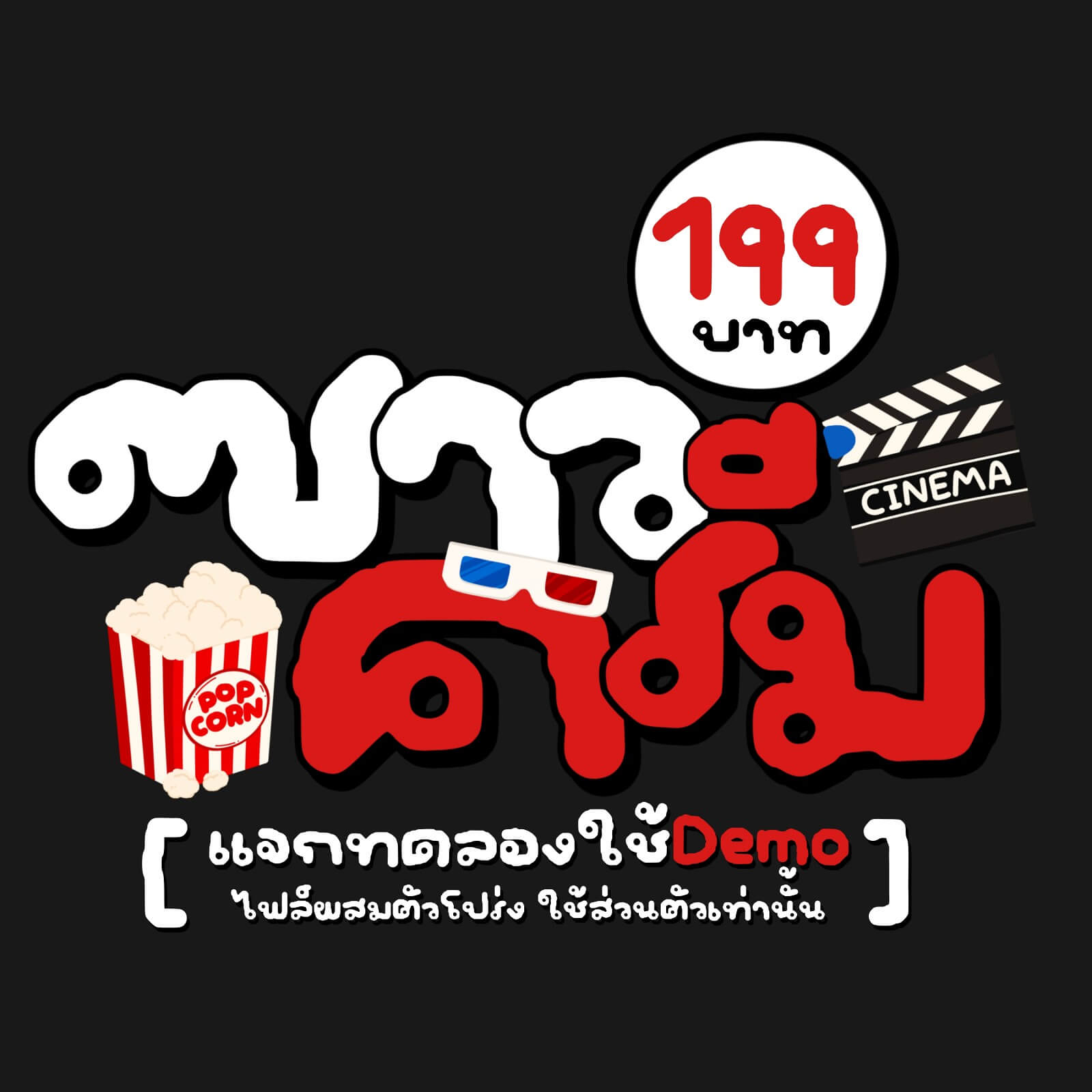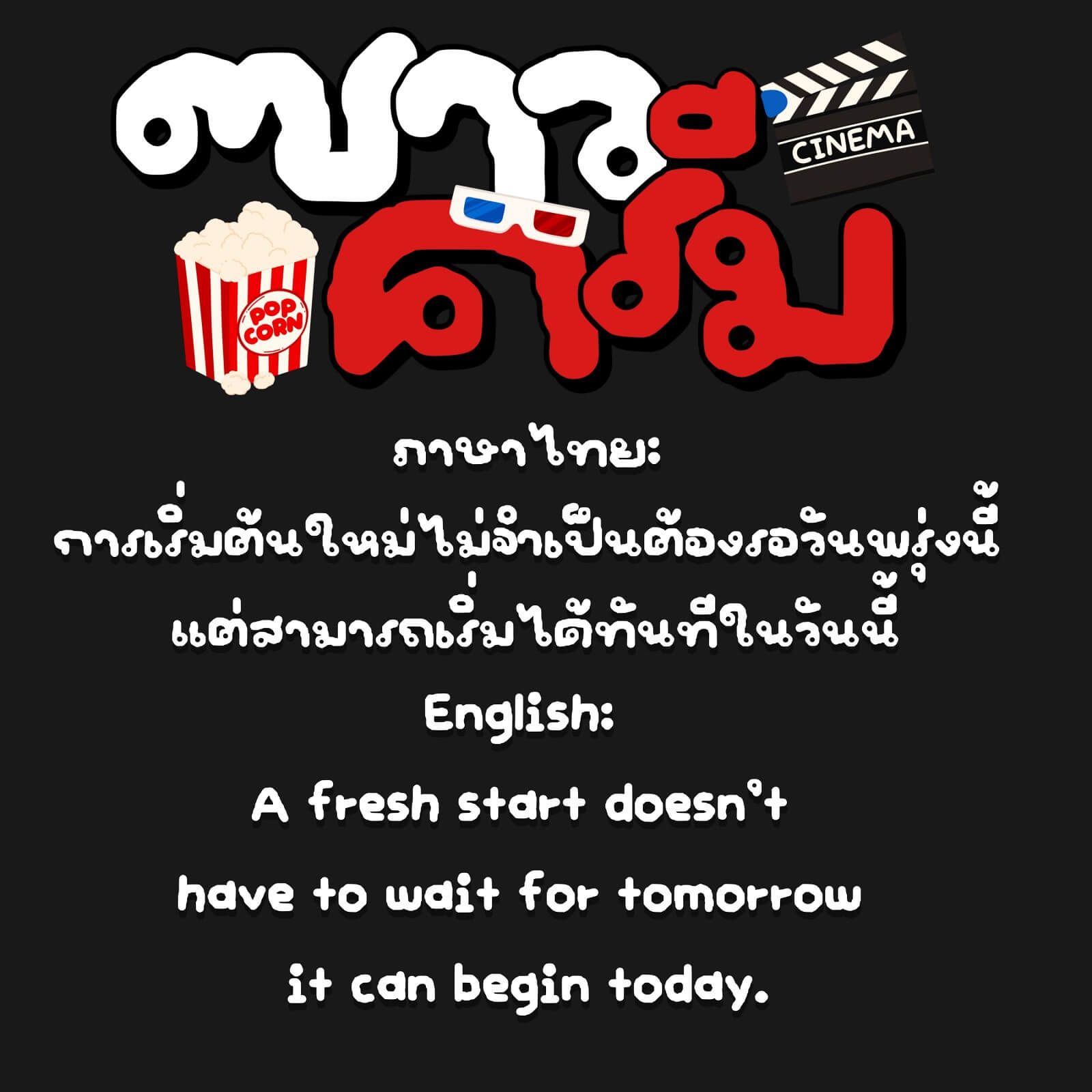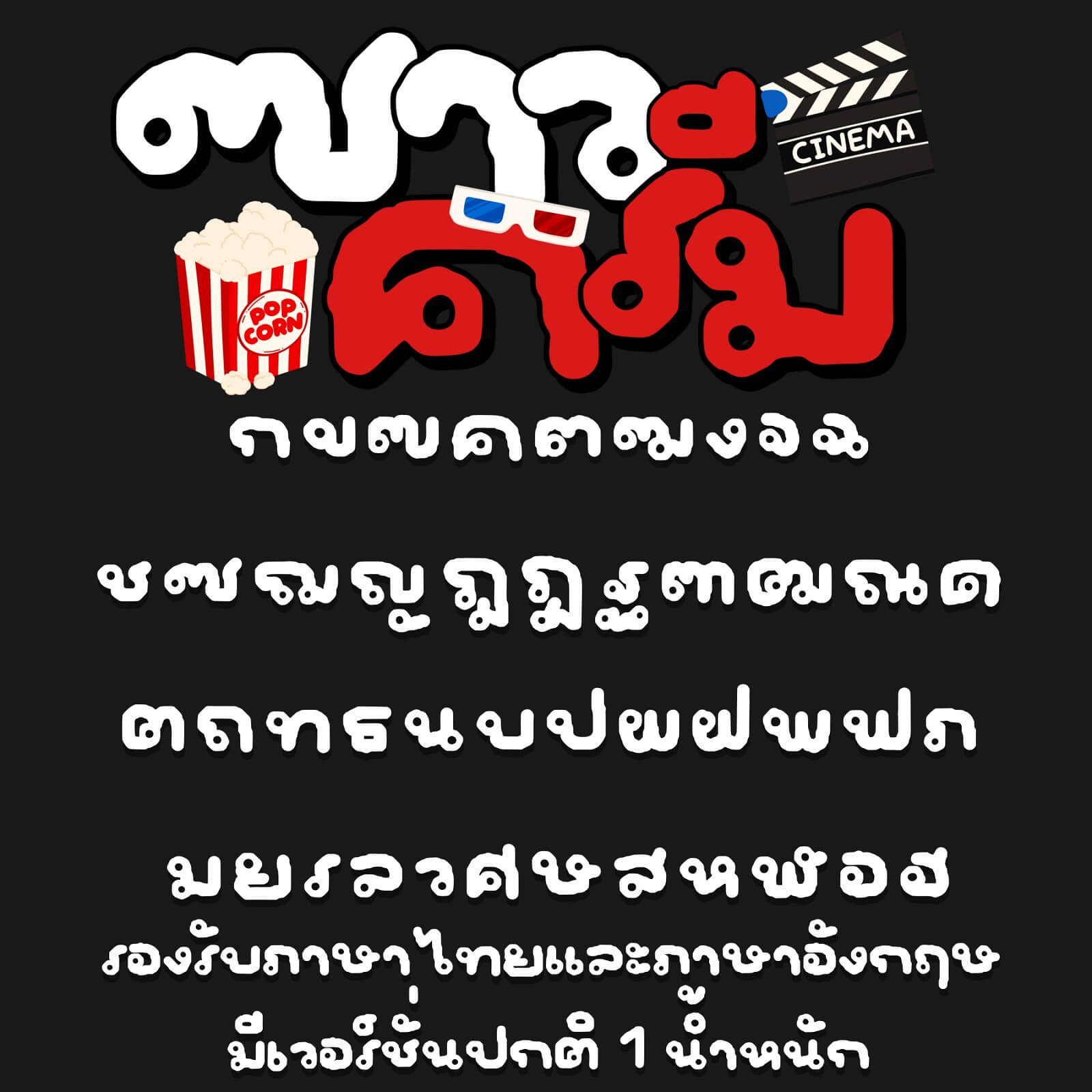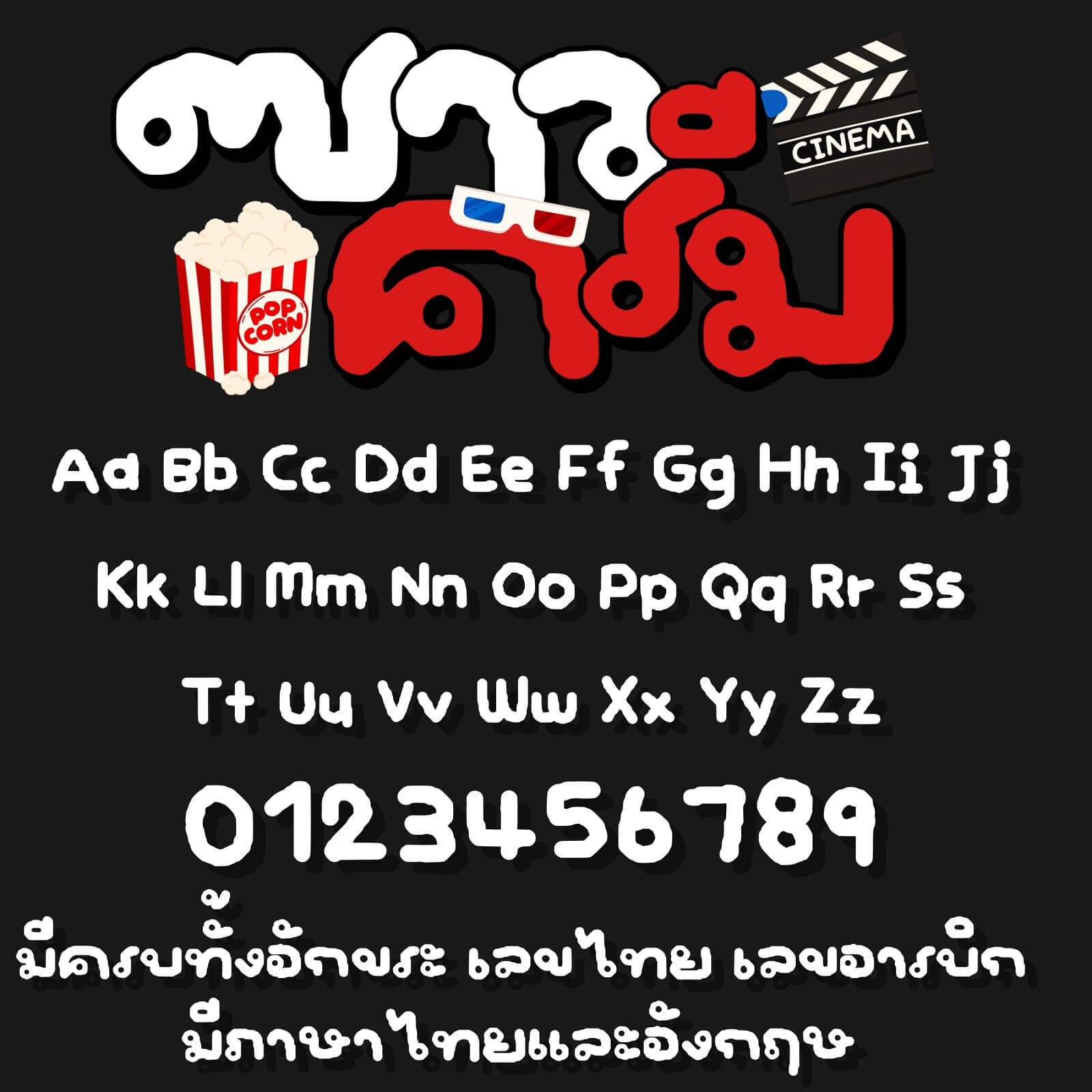
IMTYC อิมซาวครีม ฟอนต์ – นุ่มฟูหยักๆ น่ารักกกก
เหมาะกับทุกสายครีเอเตอร์ ไม่ว่าจะใช้ทำป้าย ข้อความ โพสต์ หรือคอนเทนต์น่ารักๆ
อิมซาวครีม (IMTYC SourCream)